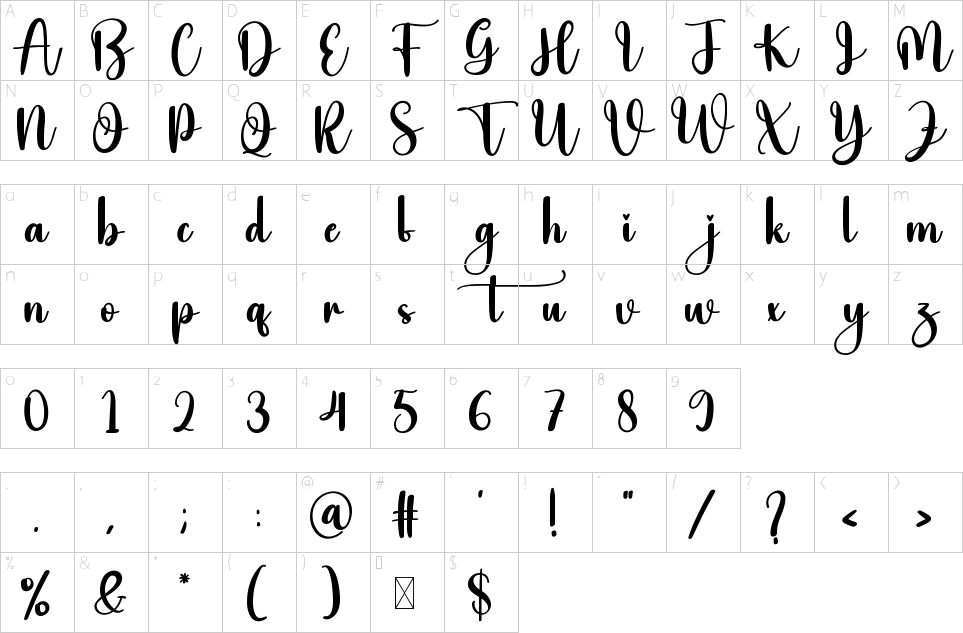
Descubra o charme da Author font, uma opção gratuita e elegante para seus projetos digitais. Desenvolvida pelo designer scratchones, esta fonte foi projetada para criar textos com um estilo minimalista e confortável. Com sua simplicidade e beleza, a Author font é perfeita para designers gráficos, escritores e profissionais digitais que desejam uma opção de fonte limpa e fácil de usar. Com uma baixa demanda, esta fonte é uma ótima opção para quem busca por recursos gratuitos. Aproveite e baixe a Author font para Windows e Mac, com uma facilidade de uso e estilo único.